26款精选免费的英文手写字体收集与打包下载 (英文签名字体)
在一些网页设计或者平面设计中,我们经常可以见到一些非常不错的 手写/涂鸦 风格的字体,它们常常能让整个作品看起来更有 Feel!或者,在你的邮件、文档、设计作品中加入一个酷酷的手写签名,看起来也会特别专业。譬如帮MM们修图之后加上一个酷酷的手写签名,那简直是帅爆了!
Jellyka – Estrya’s Handwriting
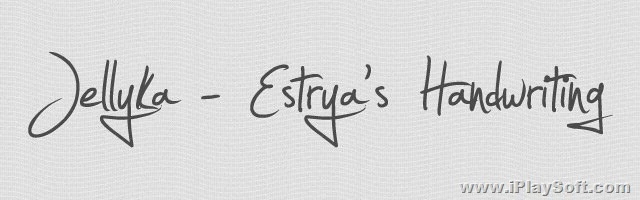
Jenna Sue
Christopher Hand
Honey Script
Angelina
James Fajardo
Journal
Hand of Sean
Throw My Hands Up in the Air
Rolina
Note this!
Post-it Penscript
Mawns Handwriting
FFF Tusj
Jenny
Luna Bar
Just Me Again Down Here
PopStar Autograph
Carefree
CAC Pinafore
Designer Notes
Pirmokas
Janda Romantic
Walt Disney Script
Kylie X